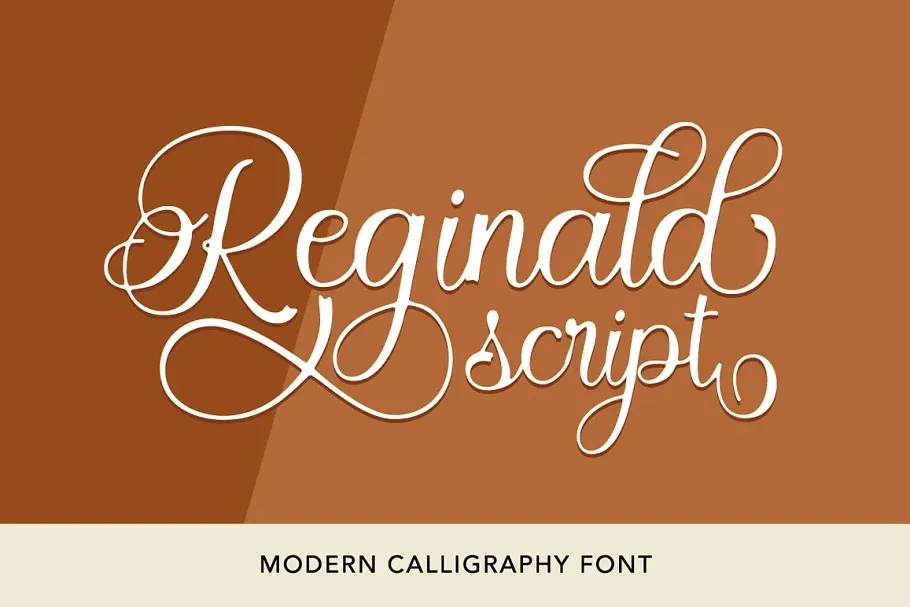
Reginald é uma bela fonte script criada com muito esforço para manter a frescura e atratividade dos traços chamados. Foi desenhado pelo talentoso designer Solidtype, resultando num estilo vibrante e elegante que se destaca entre as outras. Este script traz um conjunto diversificado de recursos, incluindo alternativas estilizadas para letras iniciais e terminais, ligações e suporte internacional para muitas línguas ocidentais. A inclusão do suporte linguístico garante uma versatilidade impressionante que torna Reginald perfeito para a criação de designs modernos como anúncios, logotipos, marcas, citações, cartões de convidado e convites para casamentos. Com um design irresistivelmente lindo, este font é uma opção excepcional para qualquer projeto que deseja destacar-se no mundo digital do design gráfico.